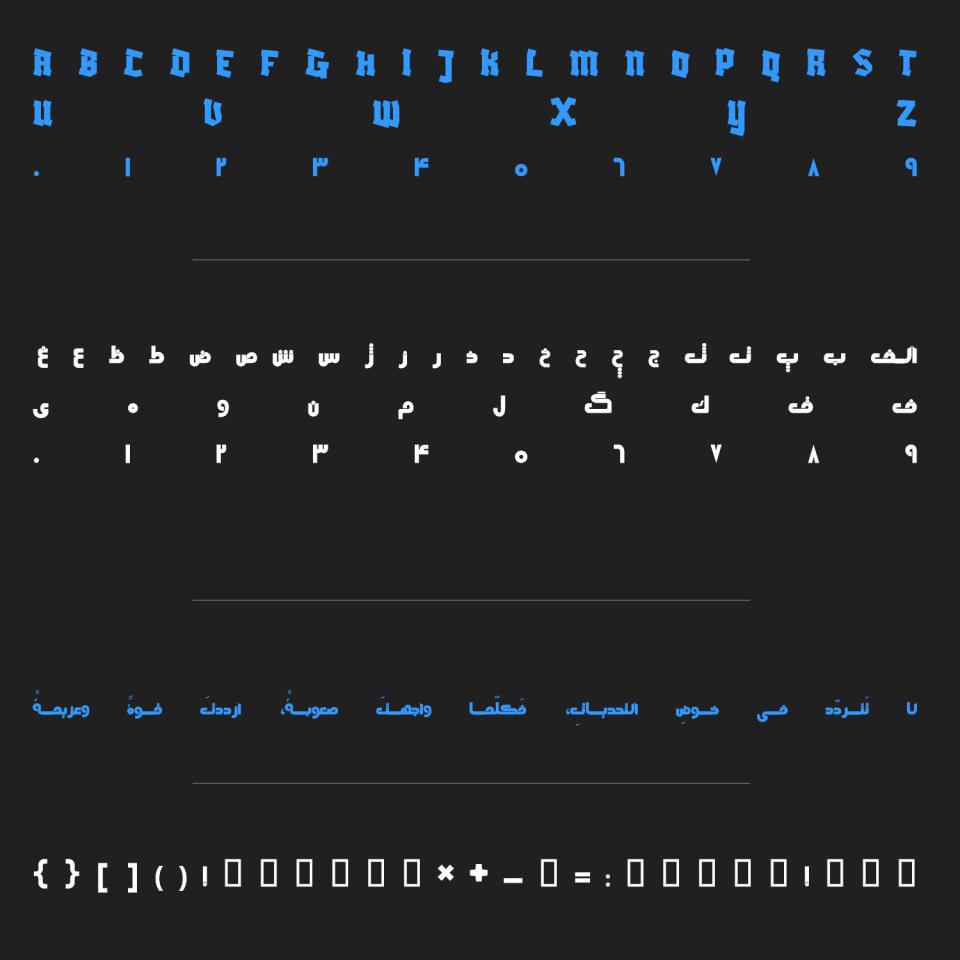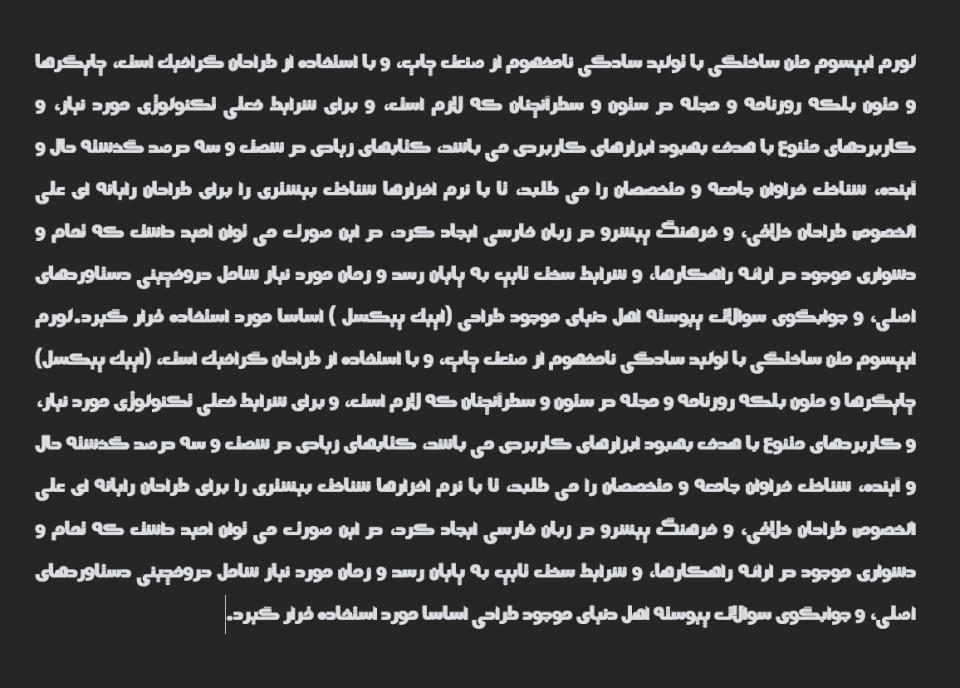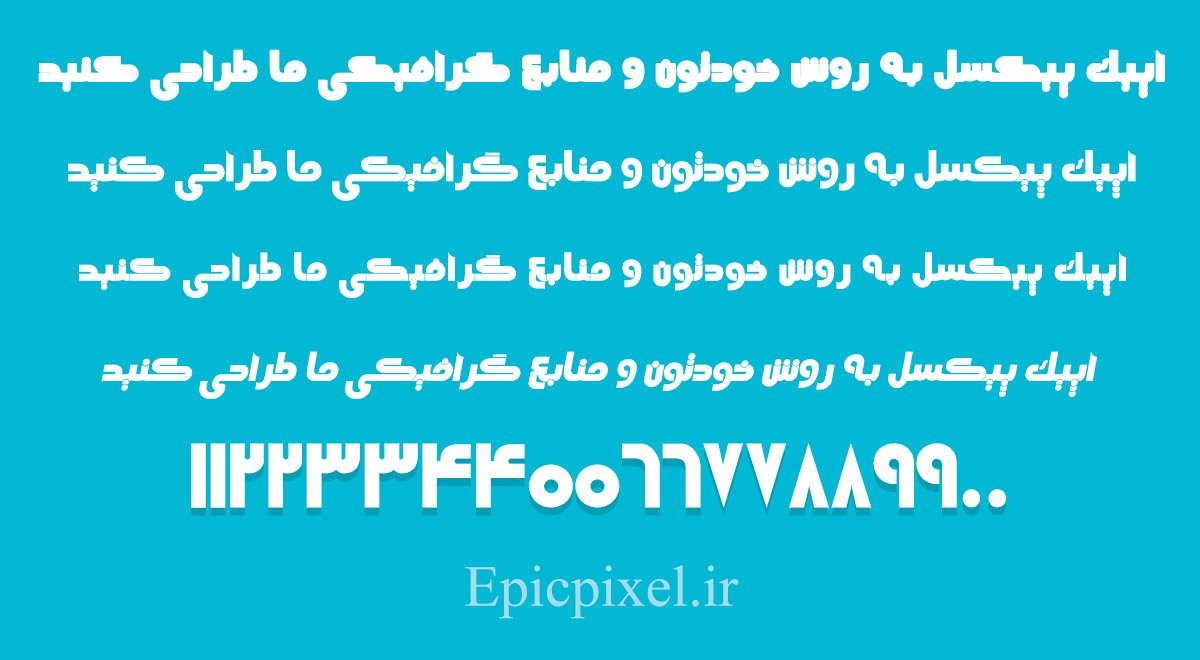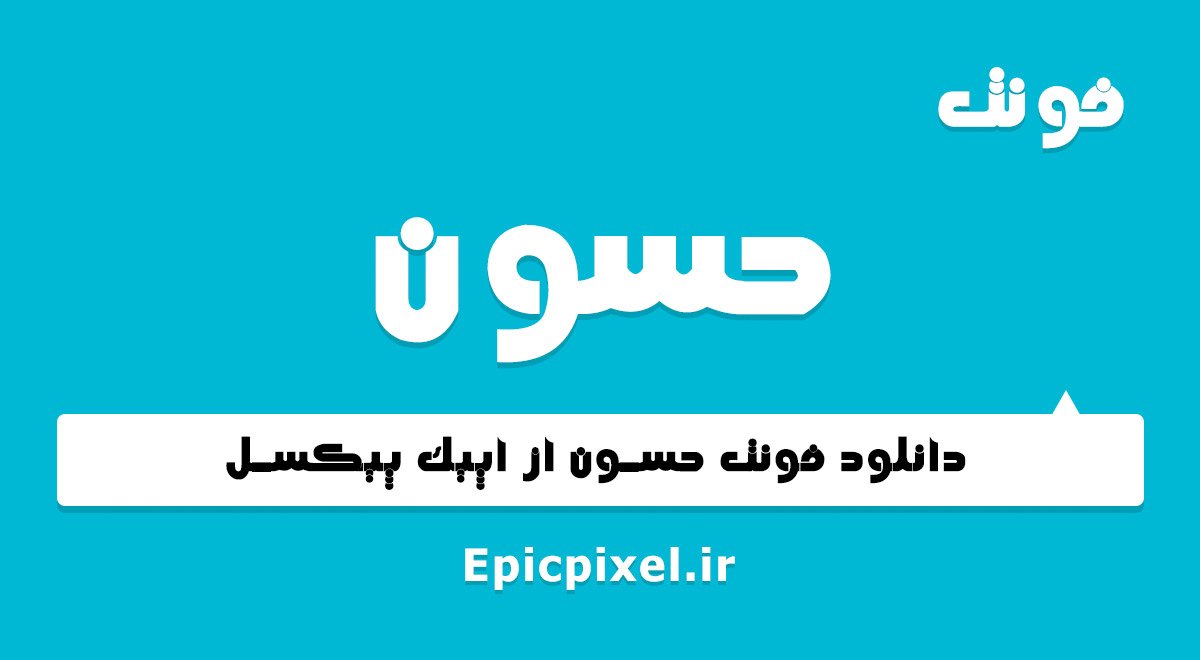
2 فونت حسون فارسی Hasoneh
فونت حسون فارسی، یک انتخاب خاص برای کسانی است که به دنبال ظرافت و تمایز در نوشته های خود هستند. این فونت با اصلاح حروف عربی و تبدیل آن ها به فرمی خواناتر و دلنشین تر برای زبان فارسی، تجربه ای متفاوت از تایپ را ارائه می دهد. یکی از ویژگی های برجسته این فونت، استفاده از نقطه های دایره ای شکل روی حروف است که به آن جلوه ای مدرن و در عین حال کلاسیک می بخشد. این نقطه ها، علاوه بر زیبایی، به خوانایی بهتر متن نیز کمک می کنند و از شلوغی و ابهام در نوشته ها می کاهند.
اگر به دنبال فونتی هستید که هم در طراحی های چاپی و هم در محیط های دیجیتال بدرخشد، حسون فارسی گزینه ای ایده آل است. این فونت به خوبی در عناوین، متون کوتاه و حتی لوگوها خود را نشان می دهد و به کار شما هویتی منحصربه فرد می بخشد. البته باید توجه داشت که این فونت رایگان نیست و برای استفاده از آن نیاز به خرید لایسنس دارید. این موضوع می تواند برای برخی کاربران محدودیت ایجاد کند، اما در نظر داشته باشید که با خرید این فونت، شما در واقع صاحب یک ابزار ارزشمند و باکیفیت خواهید شد که می تواند در پروژه های مختلف به شما کمک کند.
یکی دیگر از ویژگی های این فونت، هماهنگی بالای آن با دیگر فونت های فارسی است. این ویژگی به شما این امکان را می دهد که به راحتی از حسون فارسی در کنار سایر فونت ها در یک صفحه یا طرح استفاده کنید و نگران ناهماهنگی و عدم تطابق آن ها نباشید. این امر به ویژه برای طراحان گرافیک و صفحه آراها اهمیت زیادی دارد. در نهایت، اگر به دنبال فونتی هستید که ترکیبی از زیبایی، خوانایی و کارایی را به شما ارائه دهد، فونت حسون فارسی انتخابی شایسته خواهد بود.